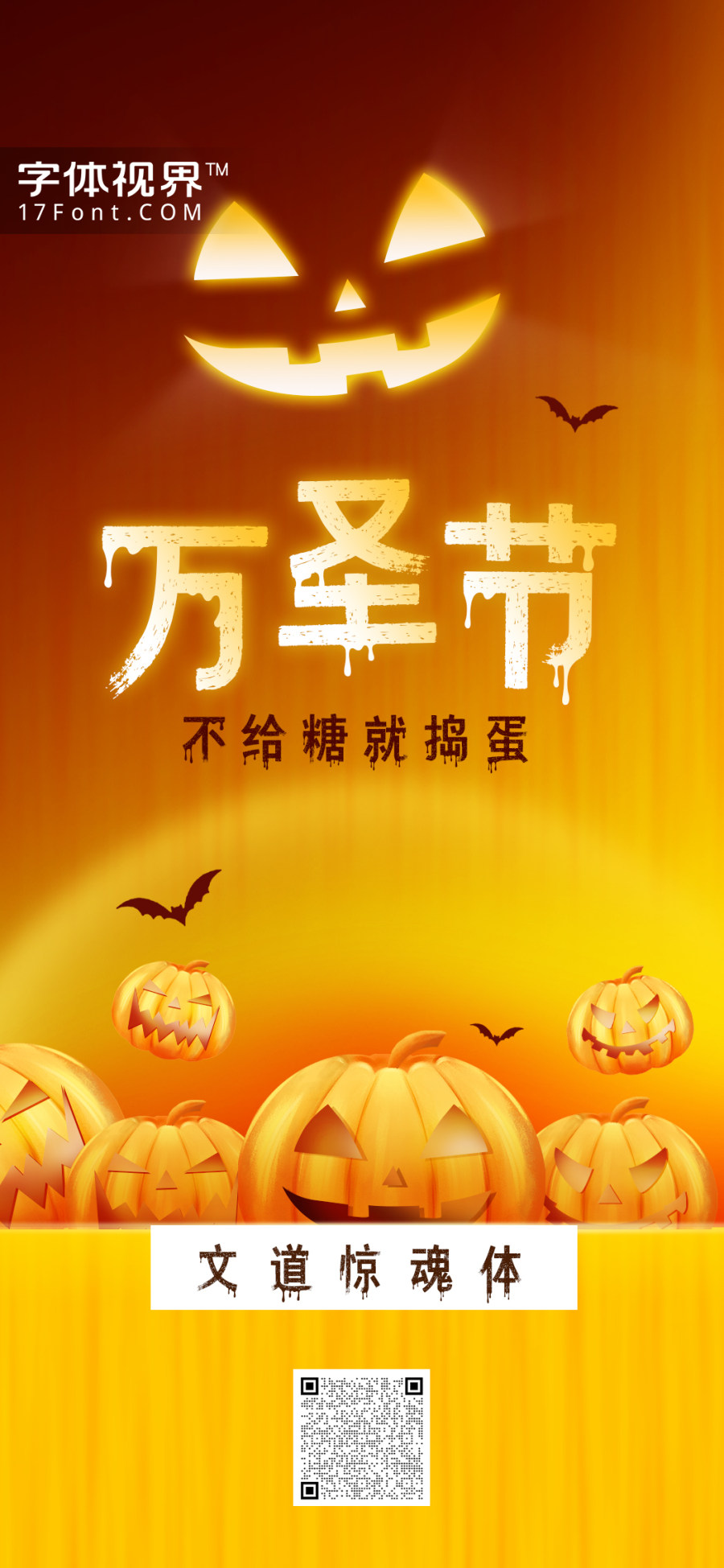
万圣节相匹配的字体推荐
万圣节就要到了,如果你想制作一张高质量的万圣节海报,除了南瓜灯、巫师帽、面具、化妆舞会、糖果、城堡等元素外,你还要拥有一款与万圣节相匹配的字体!
义启万圣体一款个性有趣的字体。字体将部分横画变形为蝙蝠的剪影,部分点画变形为雕刻着鬼脸的南瓜灯、或者有着高高的尖角的巫师帽。撇、捺画的尾端都变形为尖尖的上扬的弯钩,像是幽暗树林里的枯枝,也像是巫师帽的尖顶。有时候,恶魔的小眼睛会出现在竖画的中央,时刻等着吓人一跳。
义启万圣体
文道惊魂体是一款充满魔幻色彩,字体装饰带来奇幻的感觉,笔画与笔画之前独特的断开与连接设计,笔画首尾兼备窄度和宽度,整体不死板;笔画处理部分采用连笔方式,融合了一些手写感,简洁流畅,弧度的处理更加柔和。
文道惊魂体